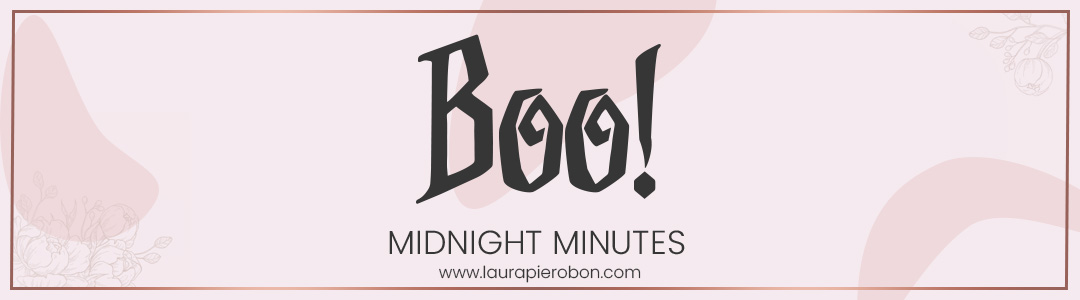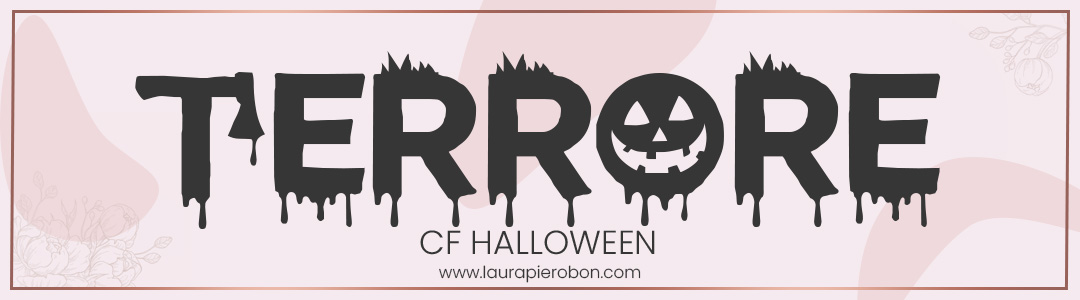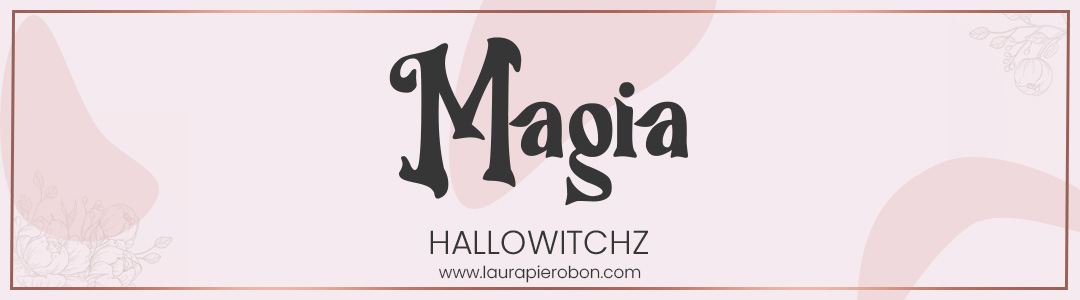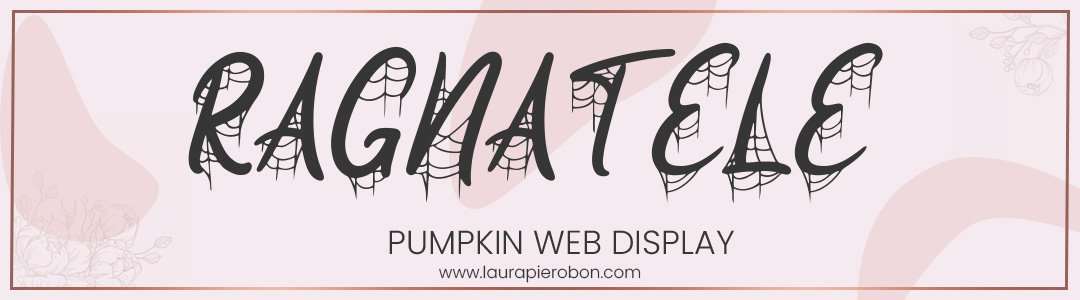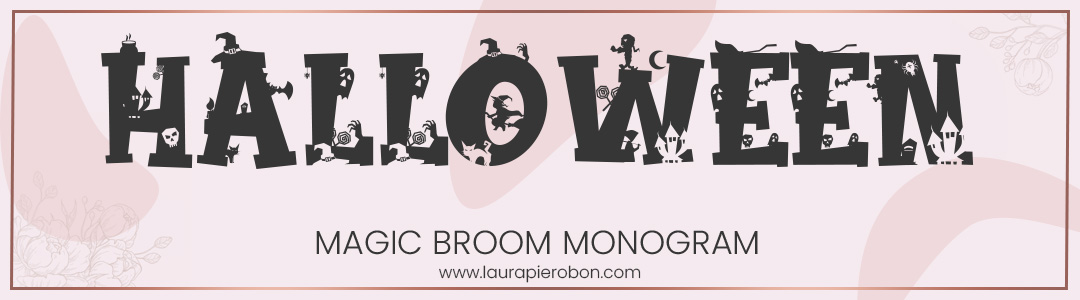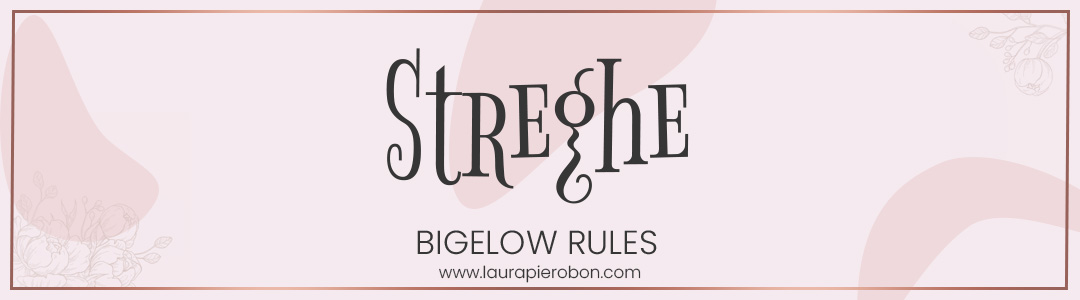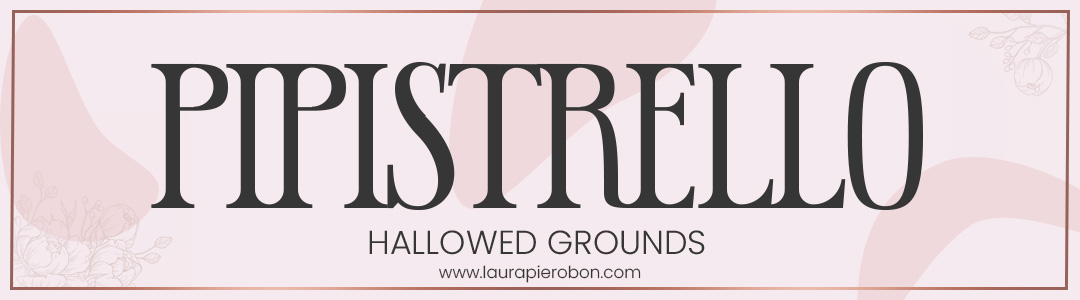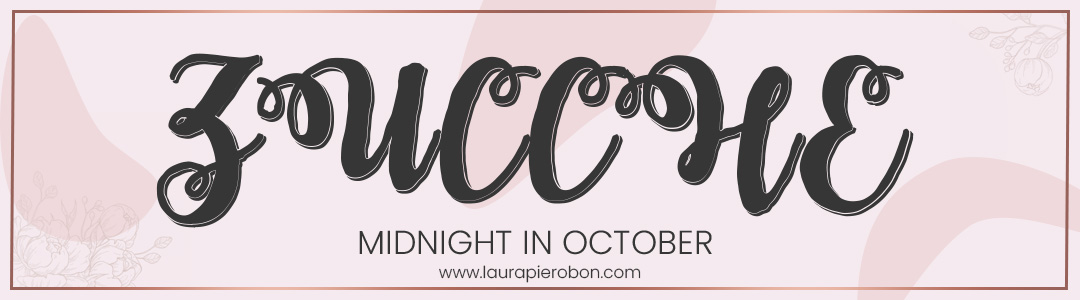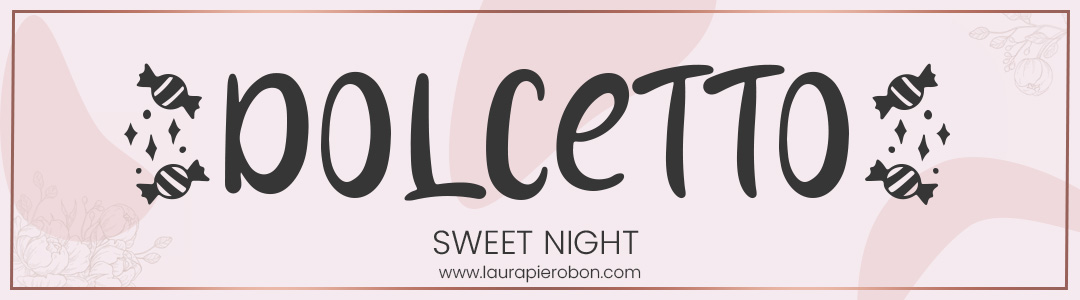
La notte più spaventosa dell’anno si avvicina… hai già pensato a come rendere i tuoi progetti davvero da brivido? 👀
Che si tratti di creare un invito per una festa, un volantino promozionale, una grafica social o semplicemente di decorare il tuo sito con un tocco a tema, il font giusto può trasformare un progetto “carino” in qualcosa di terribilmente affascinante.
Per aiutarti, ho selezionato 10 font mostruosi e gratuiti, tutti scaricabili da Dafont.com.
Sono perfetti per grafiche a tema Halloween: tra zucche, pipistrelli, scope e lettere gotiche, troverai sicuramente quello che darà vita alla tua notte da paura! 💀🕯️
💀 10 font spaventosi da provare subito
Midnight Minutes – Elegante e tenebroso, con curve gotiche perfette per titoli e copertine horror.
CF Halloween – Un font divertente e pieno di simboli iconici (zucche, ragni, cappelli da strega). Ideale per biglietti o post social giocosi.
Hallowitchz – Dal nome già un programma: un mix di magia e mistero, con tratti che ricordano le scritte incantate dei film fantasy.
Pumpkin Web Display – Decorativo e ricco di dettagli, con lettere intrecciate da ragnatele. Perfetto per titoli o volantini a tema.
Magic Broom Monogram – Un font elegante e fiabesco, ideale per chi vuole un tocco di magia più che di paura.
Bigelow Rules – Linee curve e un aspetto un po’ retrò: ricorda i vecchi manifesti dei circhi dell’orrore.
Hallowed Grounds – Scuro, gotico e intenso: perfetto per grafiche misteriose e atmosfere da brivido.
Midnight in October – Dall’aria sinistra ma sofisticata, ottimo per copertine, loghi o titoli con un’anima dark.
Sweet Night – Più dolce che spaventoso, ma ideale per progetti divertenti e per i più piccoli (magari in stile trick or treat).
Hallowed Eve – Classico e suggestivo, un font che incarna tutta l’essenza di Halloween con stile e personalità.